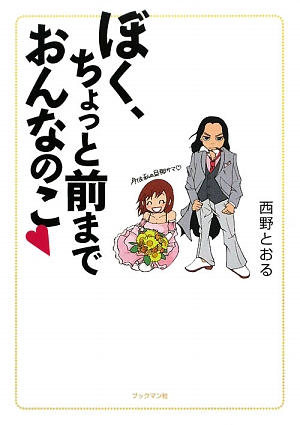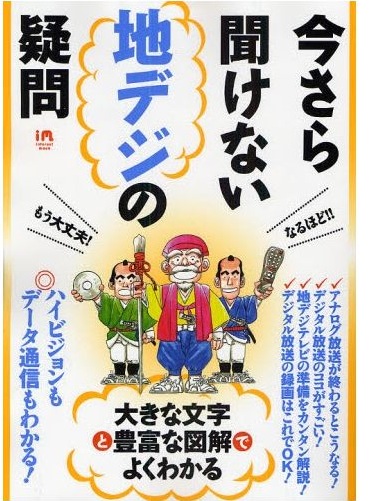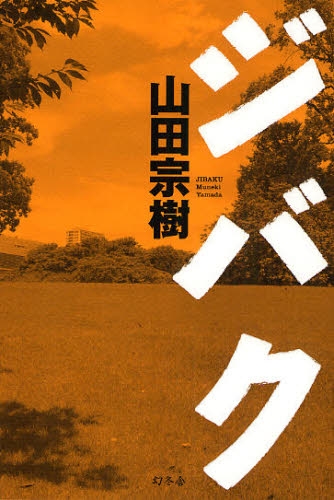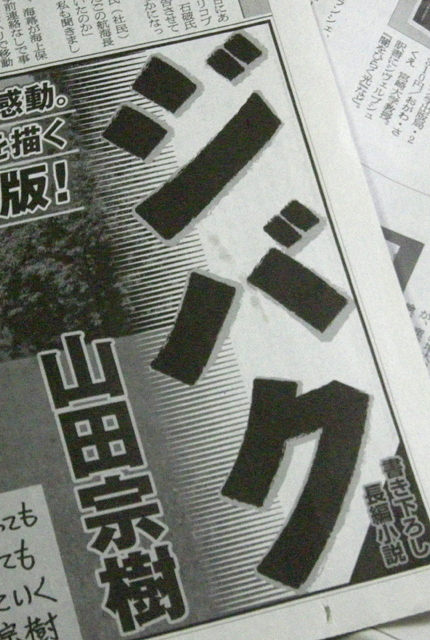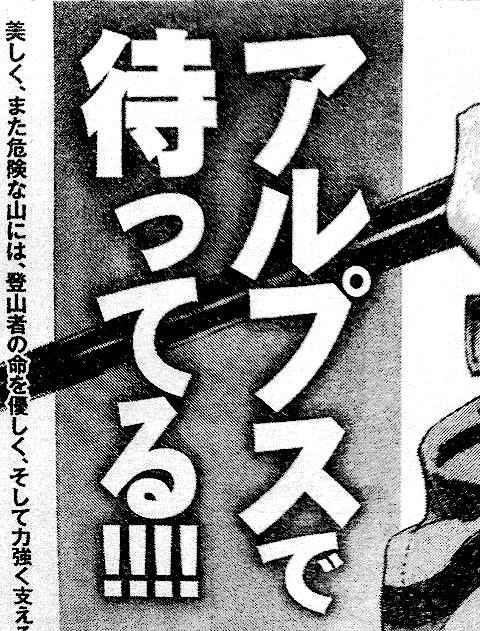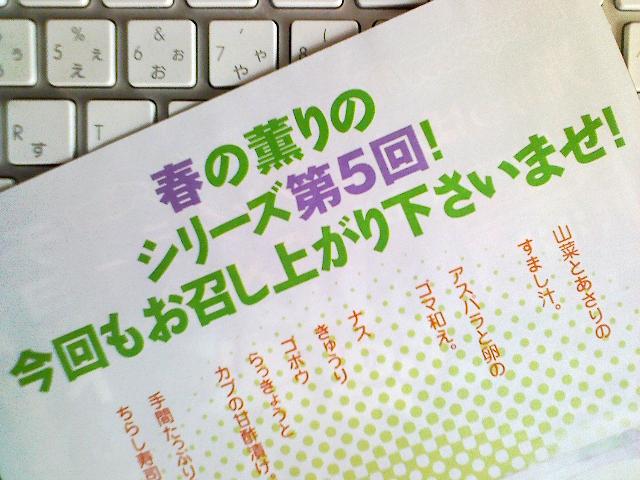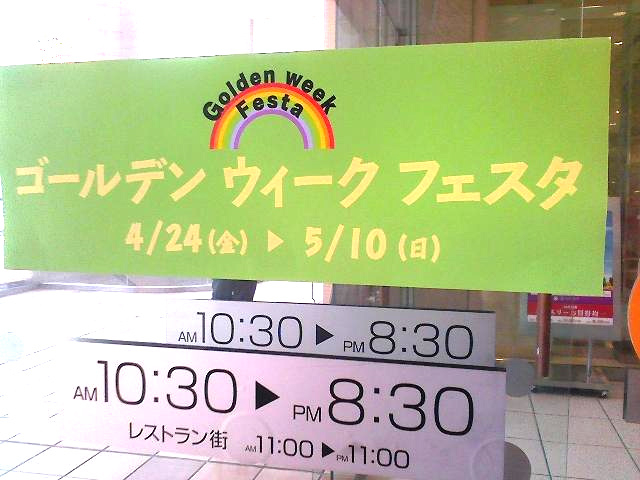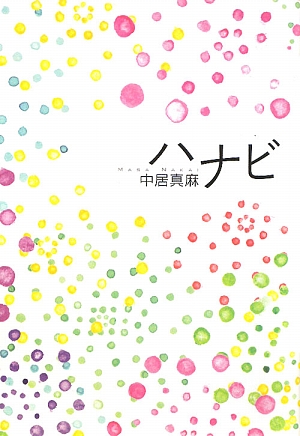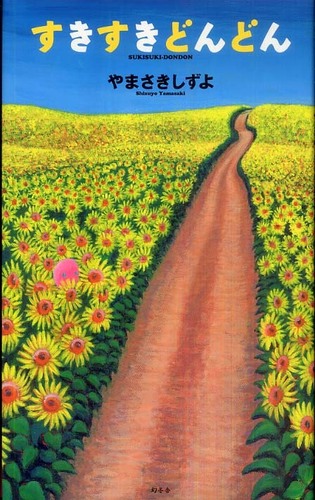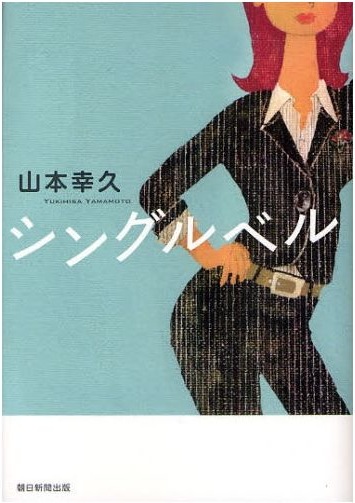
芸能雑誌のカラーページ  さとうゆたか  2011年10月18日(火) 8:23
キレイだ…。
同じデザイナーかな。
縦組みもイイよ。
通学の時の電車にて  takumi  2011年10月11日(火) 21:19  HP
いつも通学時に乗っている電車の中で見つけました。
暇があれば、いつの間にかあちこちでタイプラボフォント探している僕がいます(笑)。
小説の広告  さとうゆたか  2011年9月25日(日) 16:12
某文芸PR雑誌の本文ページに掲載されていた広告。
ロイヤルホスト(レストラン)にて…  takumi  2011年9月11日(日) 15:52  HP
レストラン『Royal Host(ロイヤルホスト)』のメニューで使われていた墨東書体です。
食べ物関係で使われると食欲そそられますね(笑)。
缶、商品名など  イワオハウス  2011年8月25日(木) 11:38  HP Mail
デザイナーの文字の選択力と
商品名に馴染んでしまうこの文字力との
ステキコラボと感じました。(3カ所に)
若手タレントの記事  さとうゆたか  2011年8月24日(水) 16:22
アイドルたちの記事や写真が載っている芸能雑誌。
意外に、墨東書体がたくさん使われていま〜す。
操業99年の自信作  さとうゆたか  2011年8月18日(木) 8:22
大正製薬グルコサミンの新聞全面広告の一部を抜粋。
料理本  さとうゆたか  2011年7月20日(水) 17:02
書名:つくりおき基本レシピ
著者:河野雅子
発行:高橋書店
表紙  さとうゆたか  2011年6月4日(土) 14:28
書名:テッドがおばあちゃんを見つけた夜
著者:ペグ・ケレット
翻訳:吉上恭太
発行:徳間書店